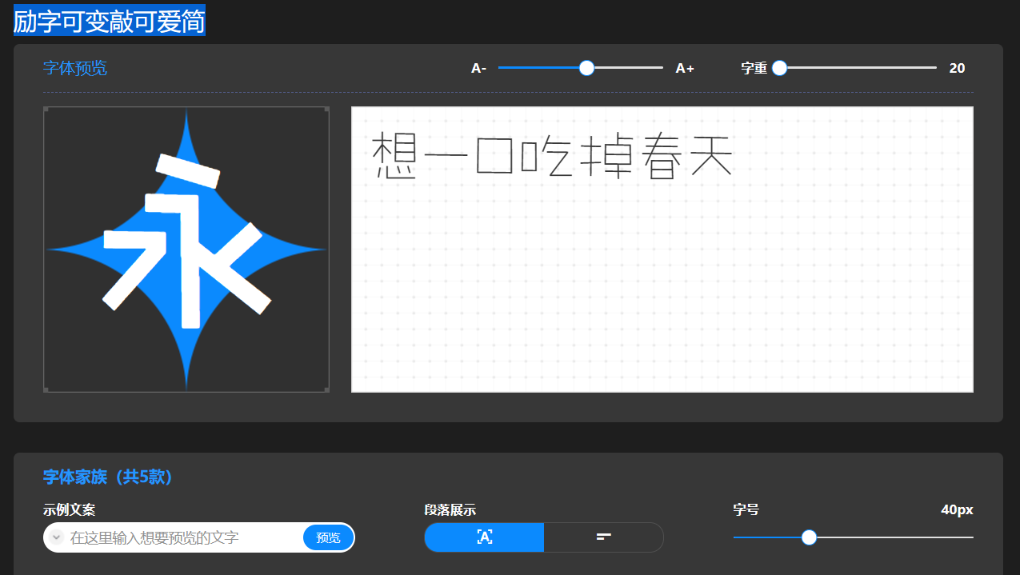
带着充满梦想与青春气息的字体,一起奔赴TFBOYS十年之约
2013年8月,三位少年怀揣梦想许下“十年之约”;2023年夏天,这个横跨十年的约定,终于随着盛夏热浪逐风而来。励字造梦局推荐2款青春励志的字体,跟随TFBOYS十年之约一起奔赴夏天~
励字志向黑简以粗细均匀的直线笔画诠释青春的极简,
笔画起止端平切、直切的设计,
折笔处采用外圆角设计,彰显流畅丝滑的青春体验。
励字敲可爱简,一款粗细均匀、简约有趣、具备手写感的直线字体。
布白空间通透,字形大小不一。整体笔画切口自然,具备手写特点,笔画设计简洁而不呆板。“弯钩笔画、钩笔画”做简化进行去钩处理。